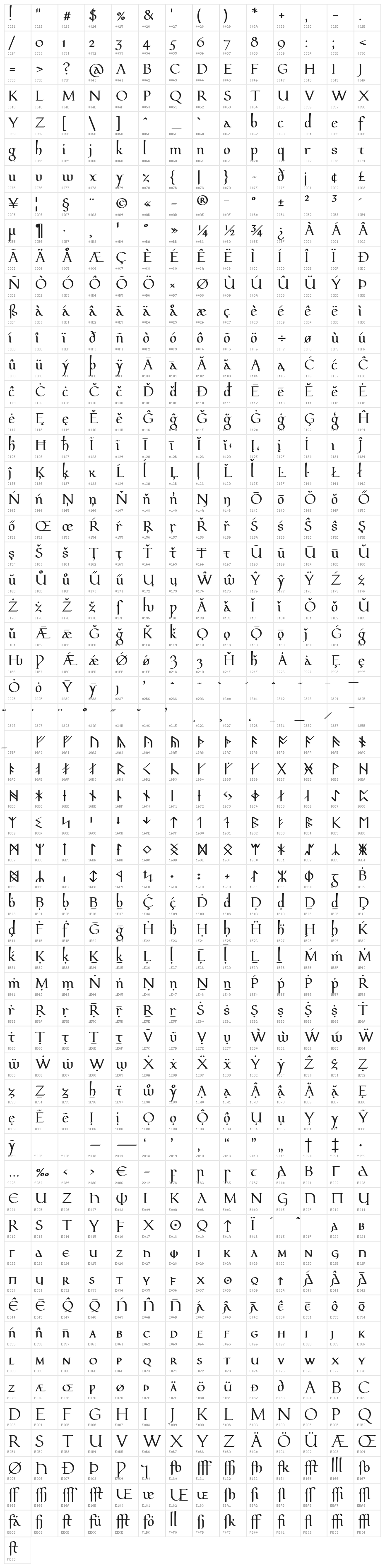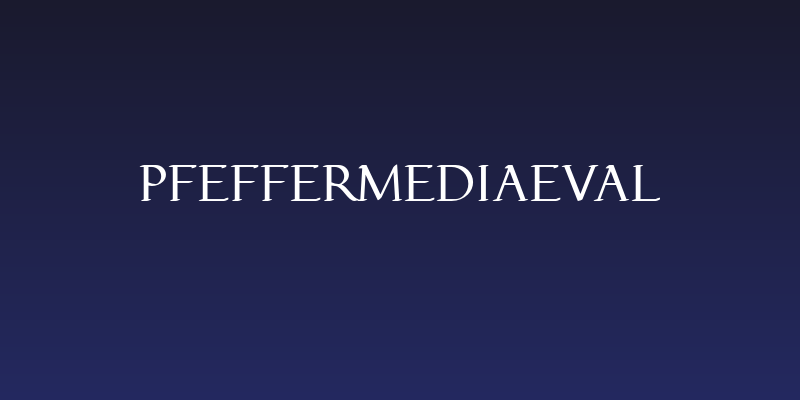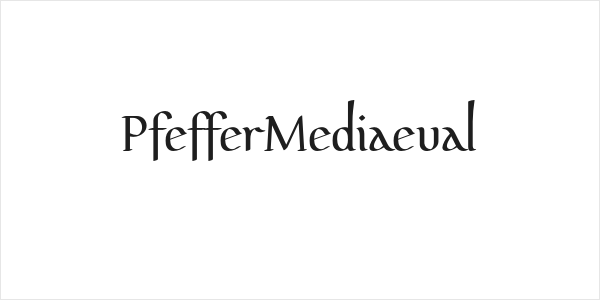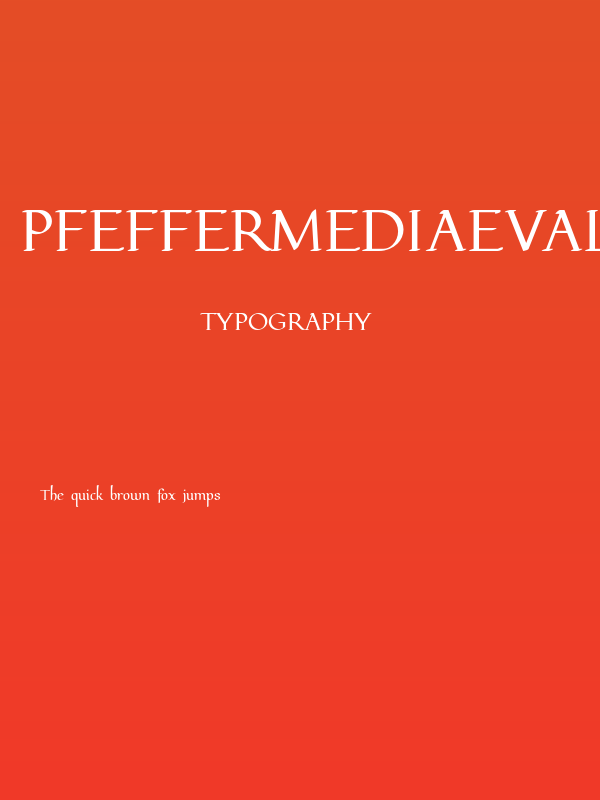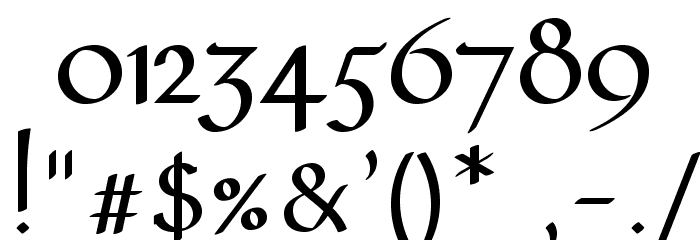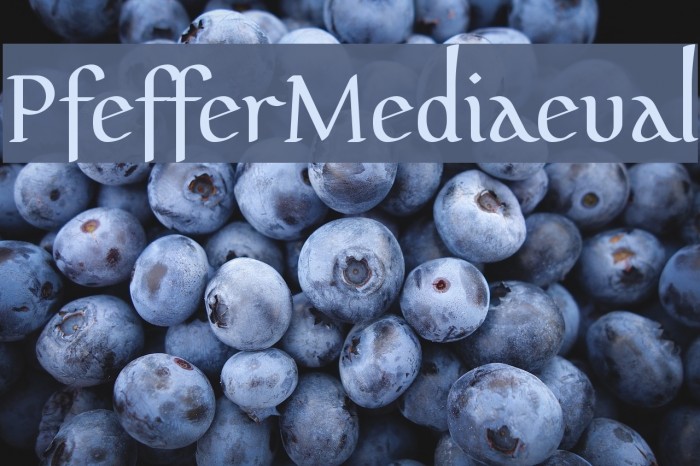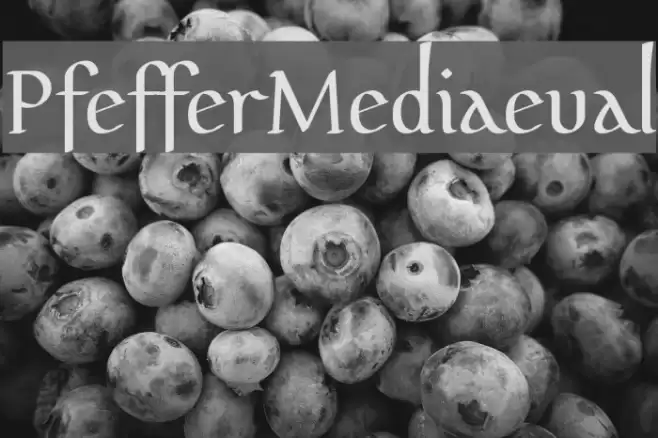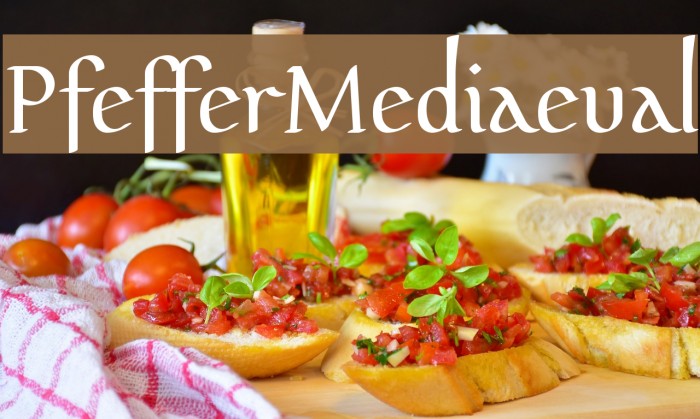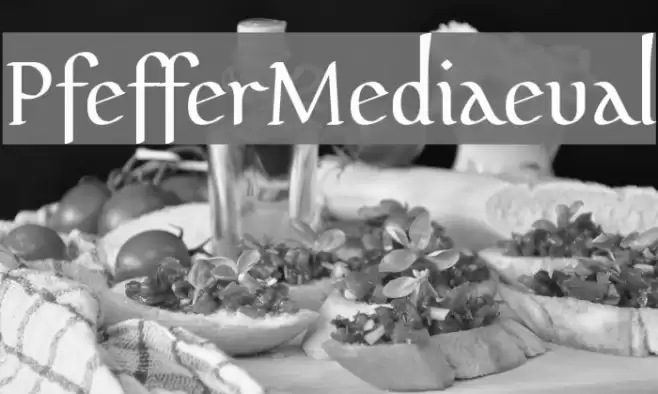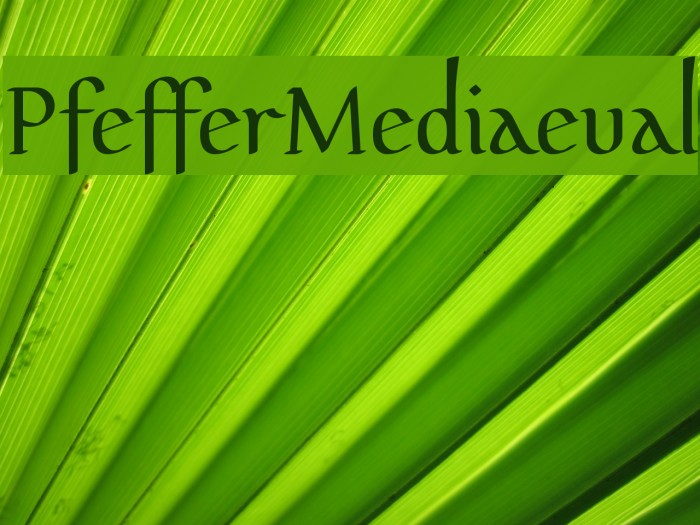
PfefferMediaeval Font
| Progetti proposti | Ideal for book covers, historical documents, invitations, and branding that requires a touch of elegance. |